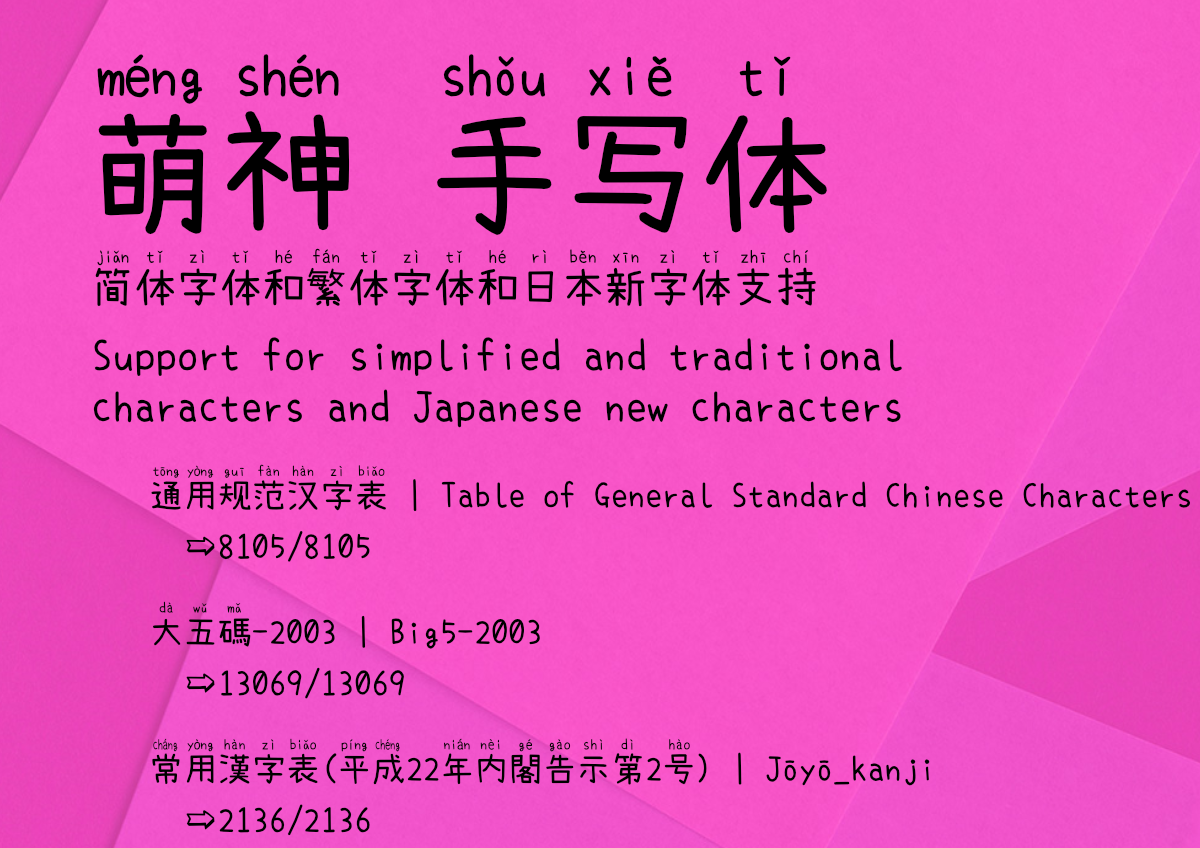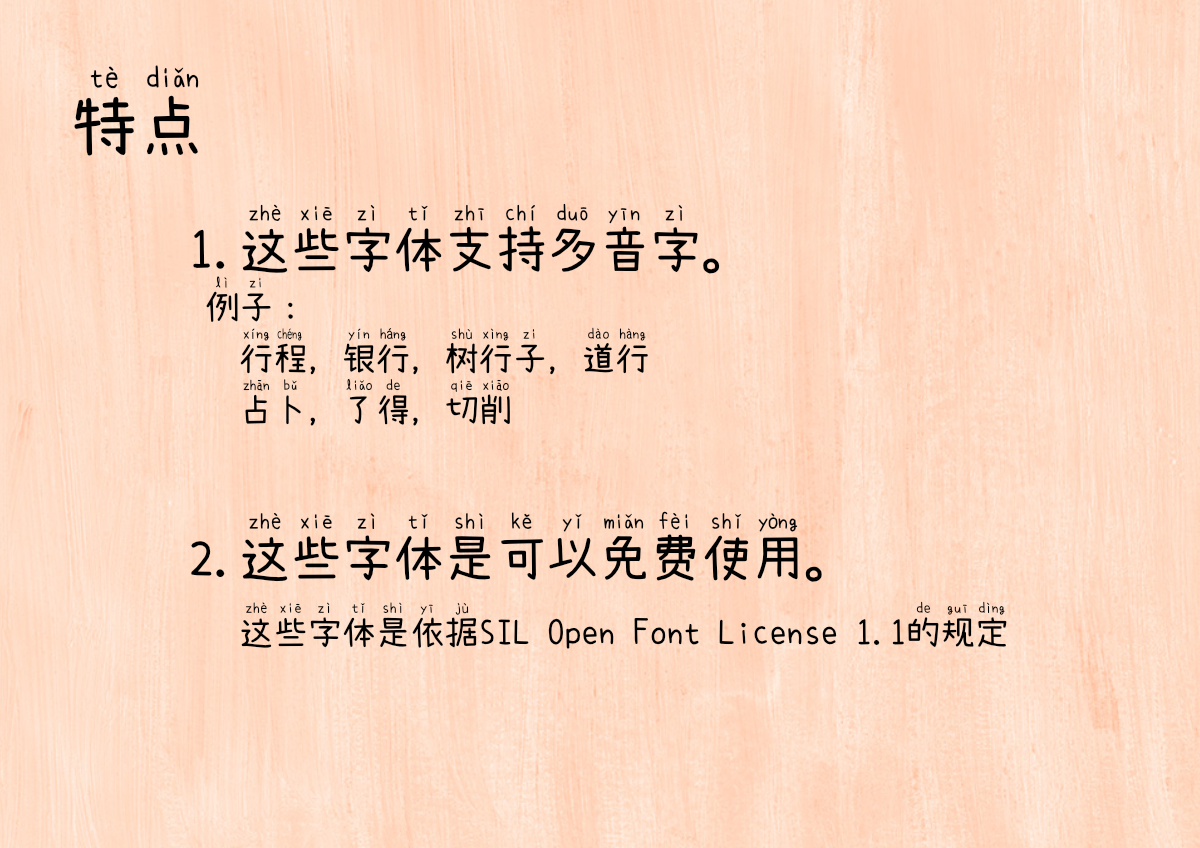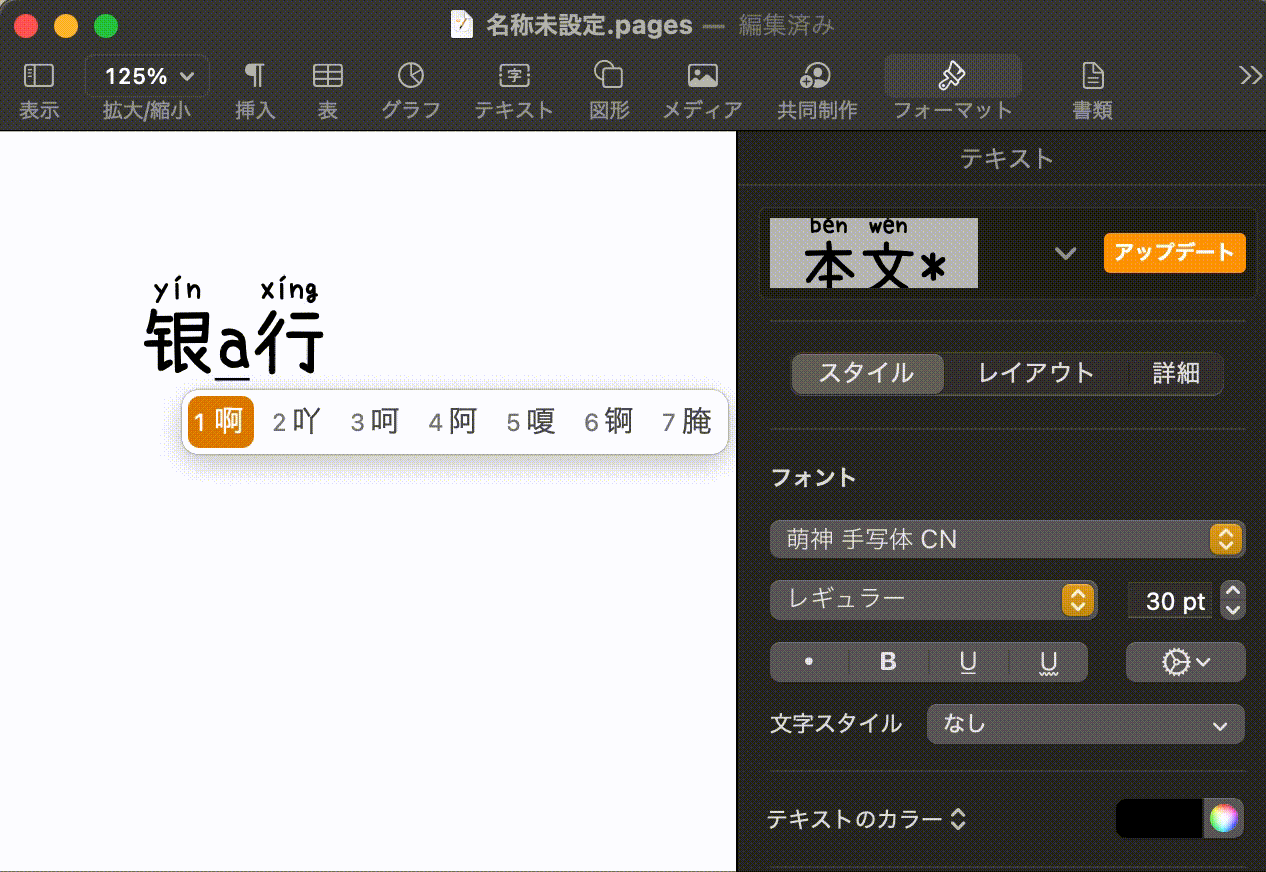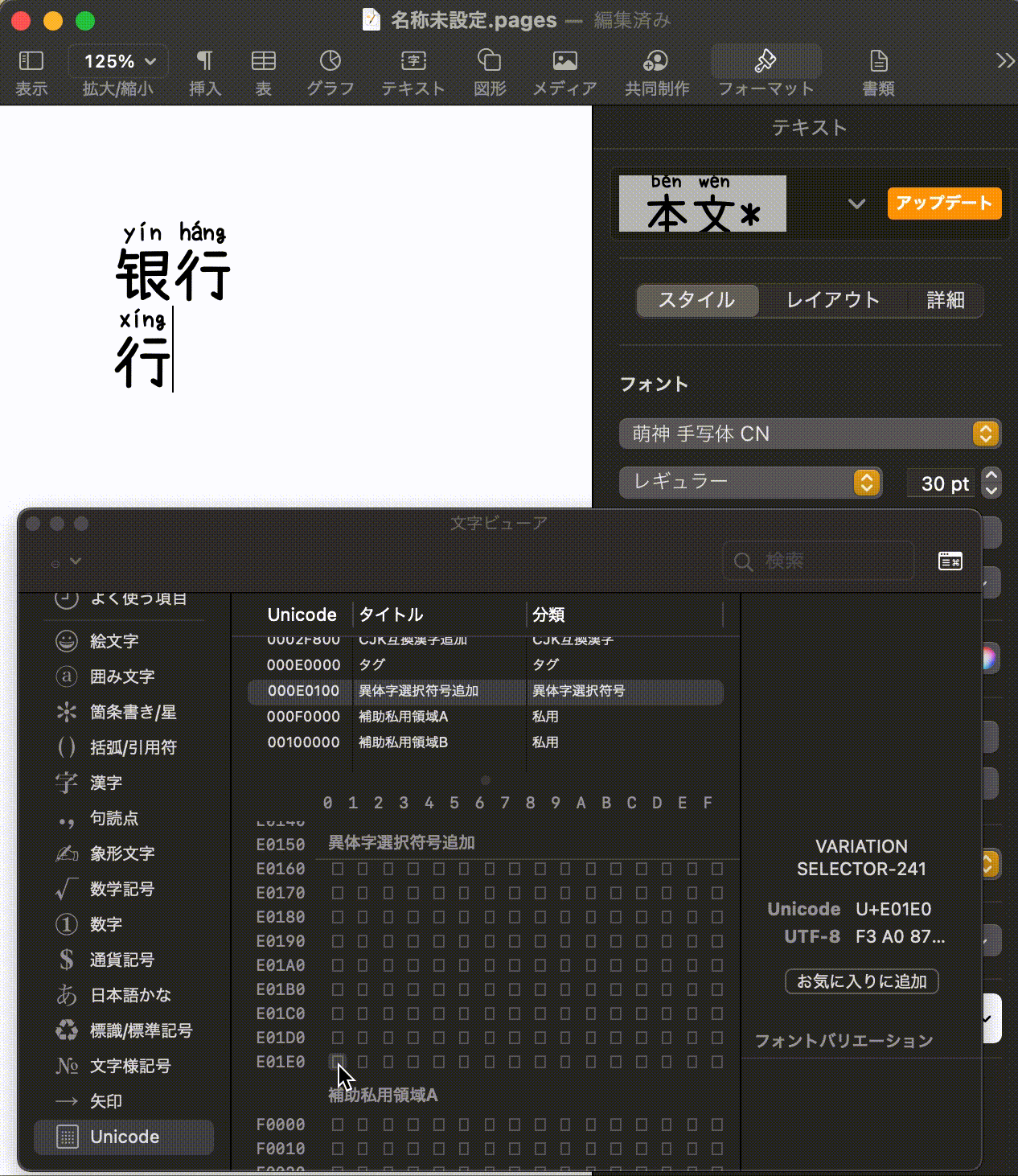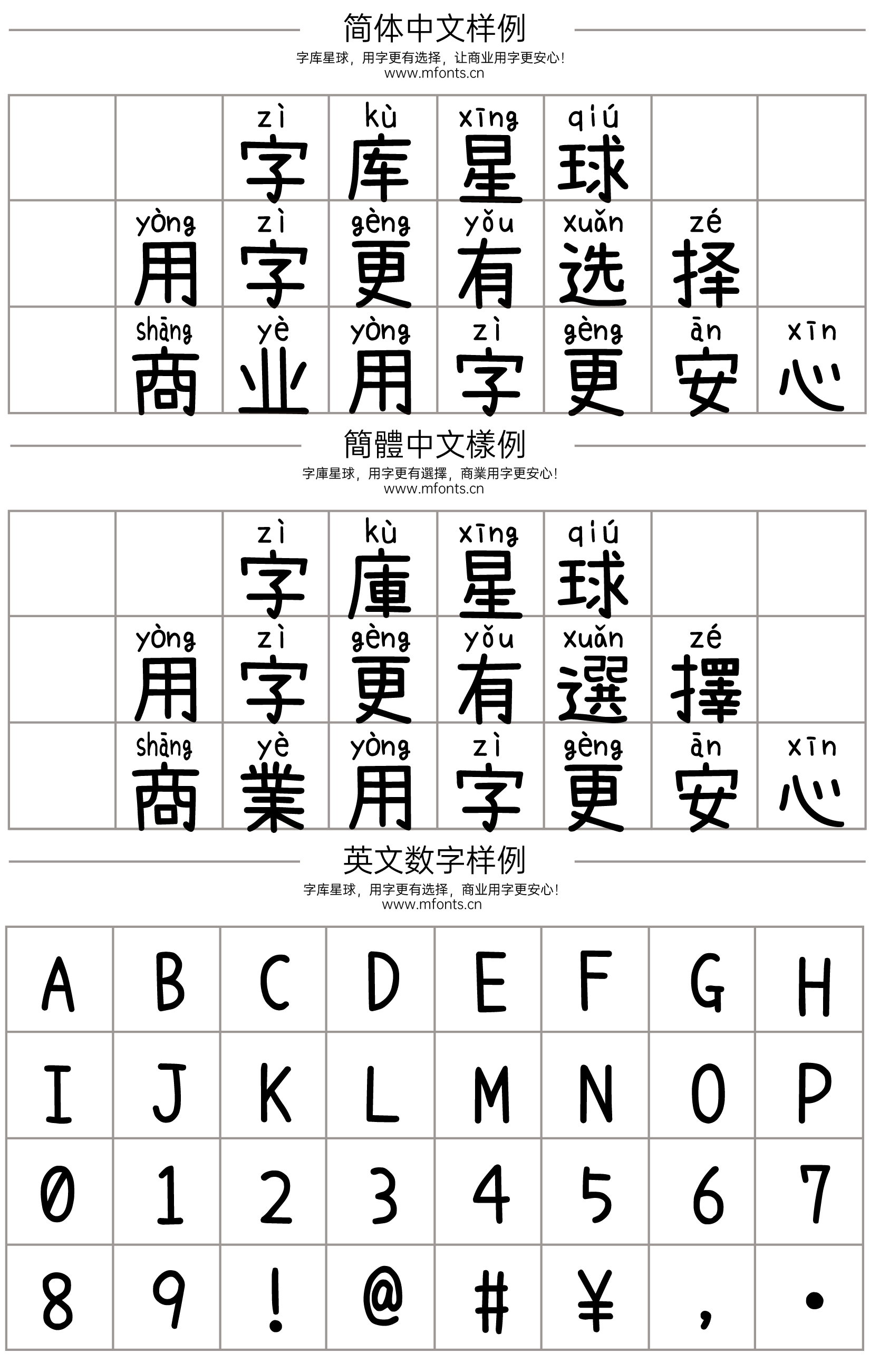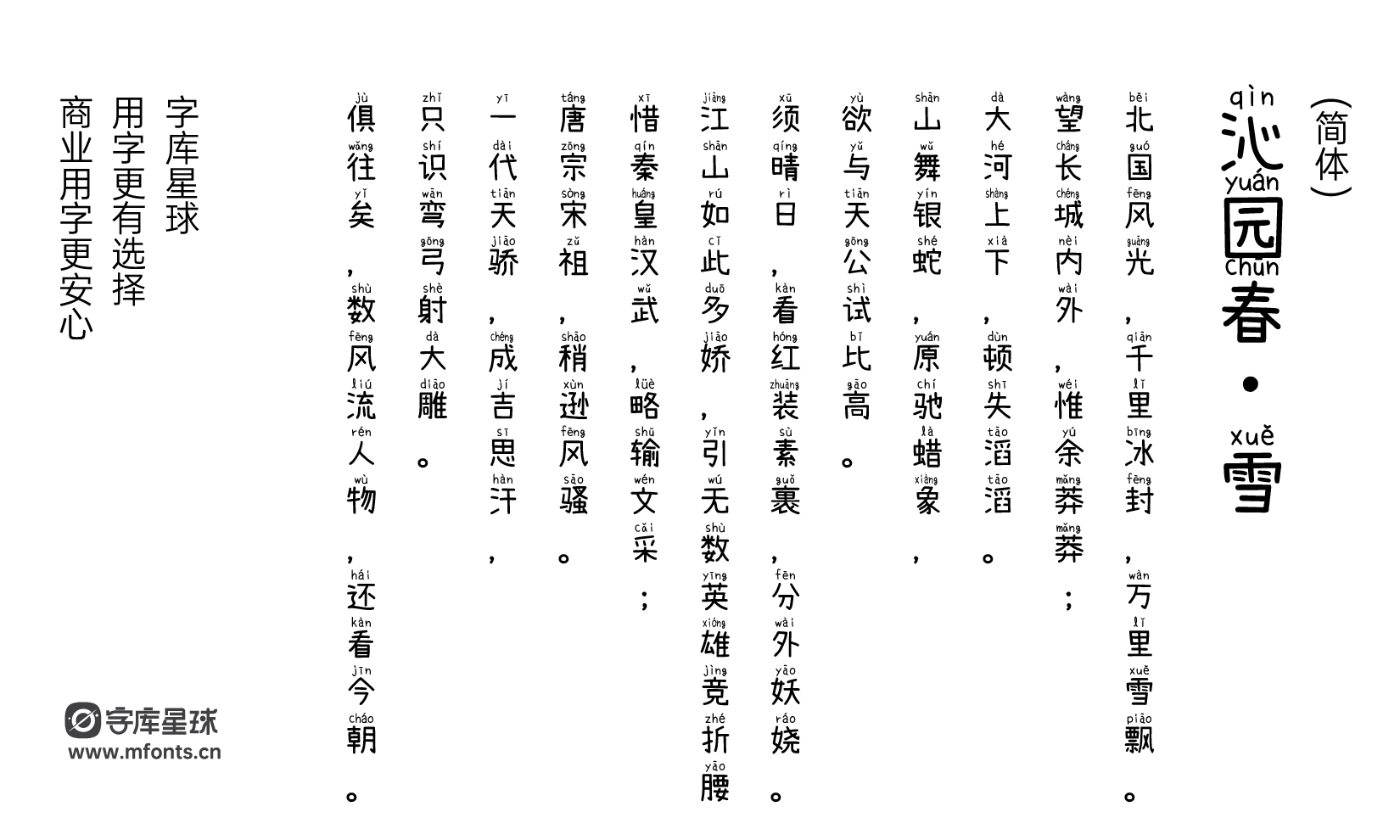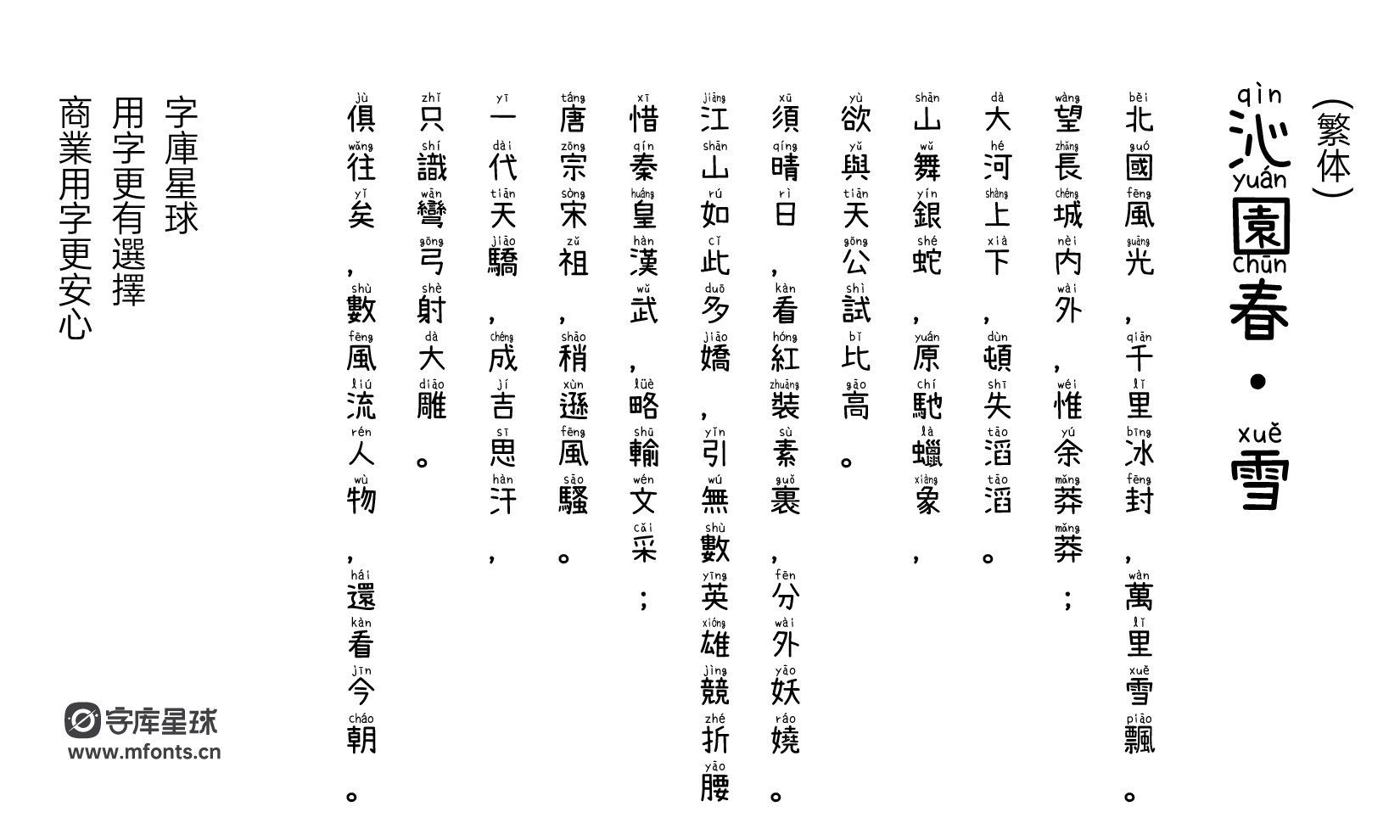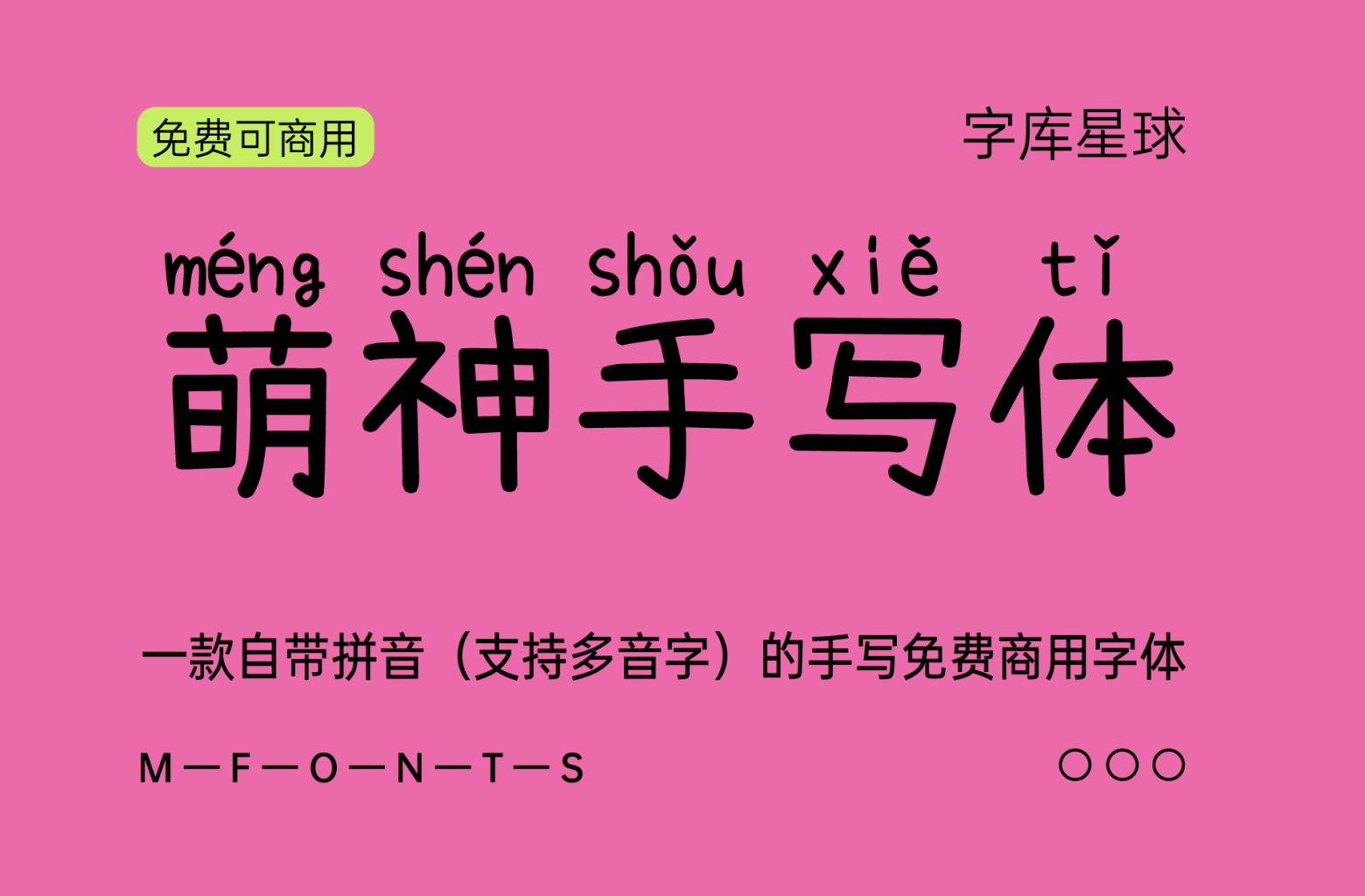
萌神手写体
萌神手写体是由小赖字体进行改造而成的一款免费商用字体,采用SIL Open Font License 1.1授权协议发布,手写风格,自带拼音,支持多音字, 适合用于帮助学生更快地学习和阅读汉语。基本上是可以显示日语、简体字和繁体字的字体,是在简体字和繁体字中加入拼音的字体的制作。
萌神项目是日本Geek中文学会的成员,利用其强大的Geek技术,制作快乐地学习中文的产品的项目。以2017年Maker Faire在深圳的展示为开端,面向各个厂家的活动中发表了产品。
萌神手写体实现了上下文替换(feature of“rclt”at GSUB)以支持多音字。另外,还可以使用Unicode IVS(表意文字变体选择器)来切换到不同的拼音。